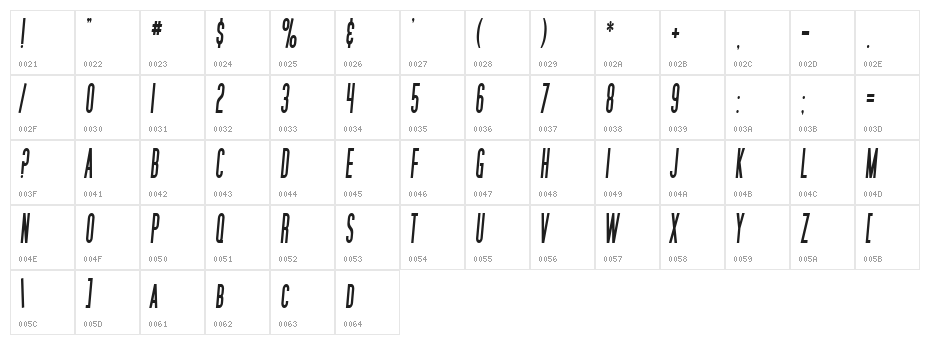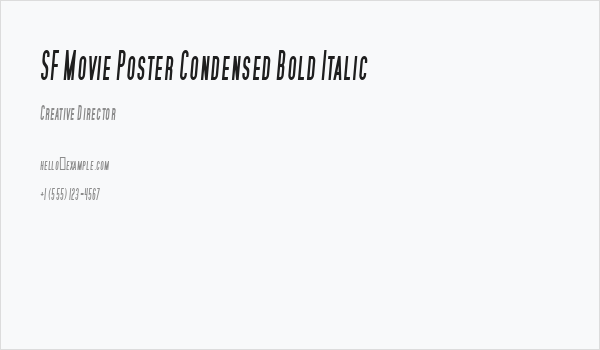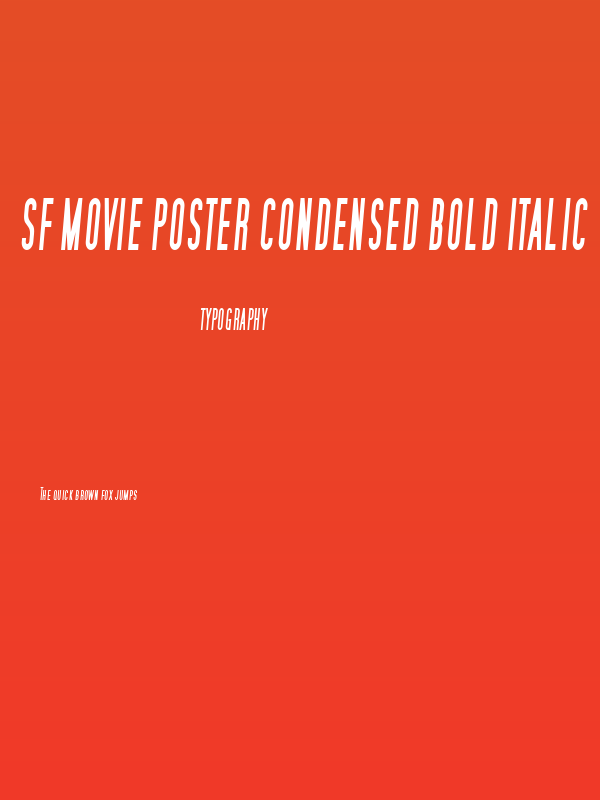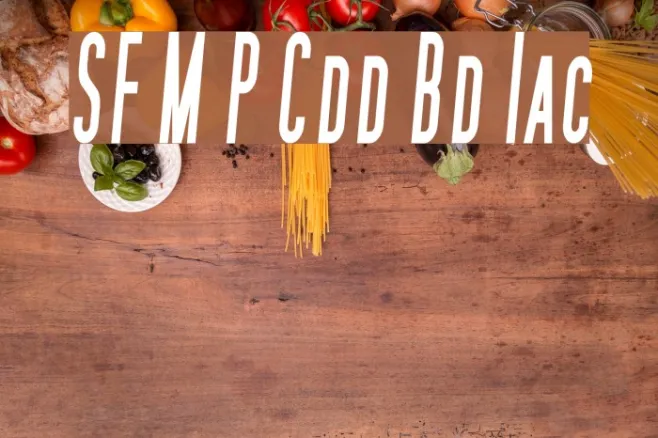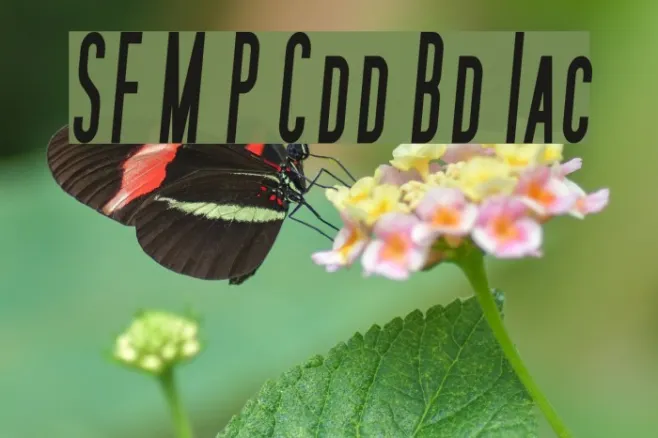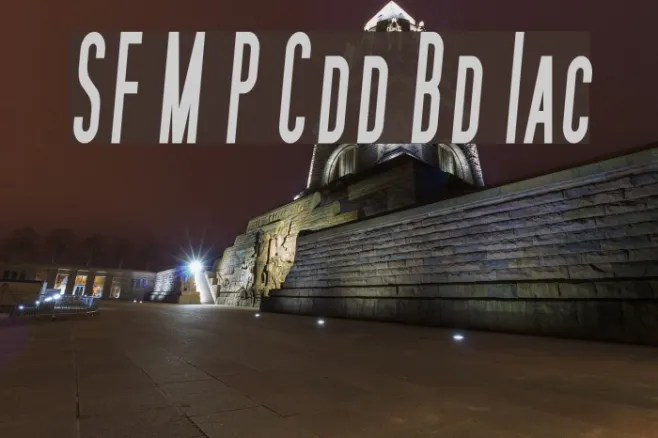
SF Movie Poster Condensed Bold Italic Font
| Vorgeschlagene Projekte | Ideal for movie posters, advertising campaigns, headlines, and branding materials that require a strong visual impact. |